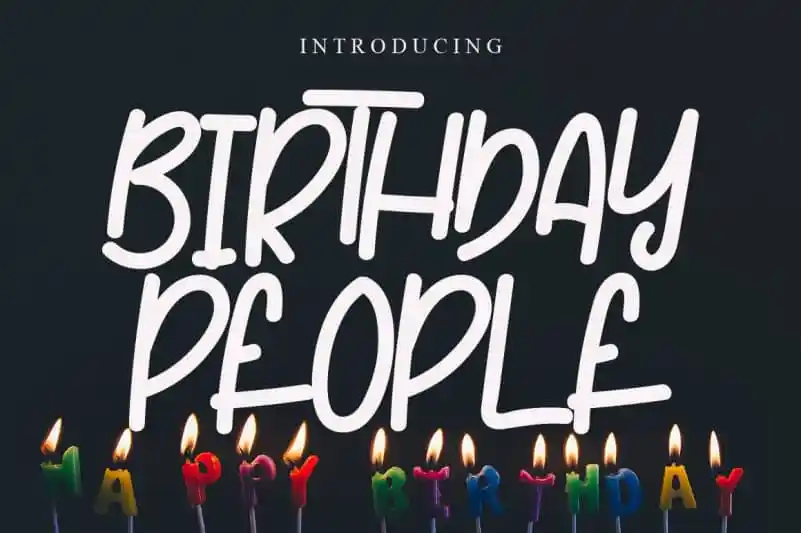
Birthday People Display Font – Download Grátis
A fonte ‘Birthday People Display Font’ é uma escolha ideal para quem busca personalidade e simplicidade na sua tipografia. Desenvolvida pela designer levincreative, esta fonte se destaca por oferecer um efeito visível com apenas poucos traços de letra, criando um resultado que parece totalmente natural, sem apelar a algo excessivamente elaborado. Suave e envolvente, ela traz uma atmosfera descontraída e autêntica que não permite confusões em qualquer projeto. Perfeita para conjugar textos com um toque de personalidade na celebração dos aniversários, seja em cartazes de festas ou até mesmo em mensagens pessoais, esta fonte destaca-se por oferecer uma aparência amigável e agradável que vai fazer seu trabalho criativo soar ainda melhor.